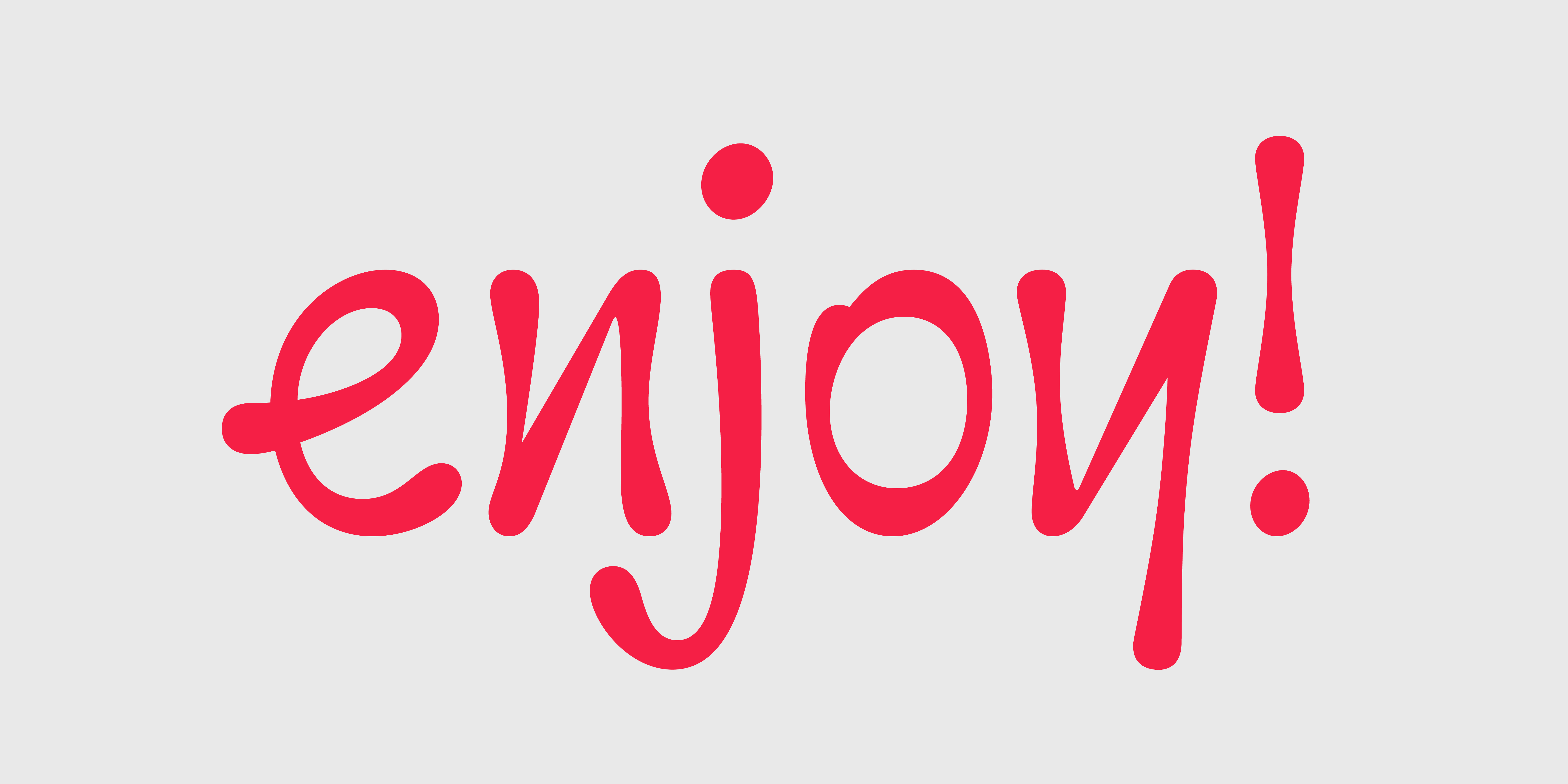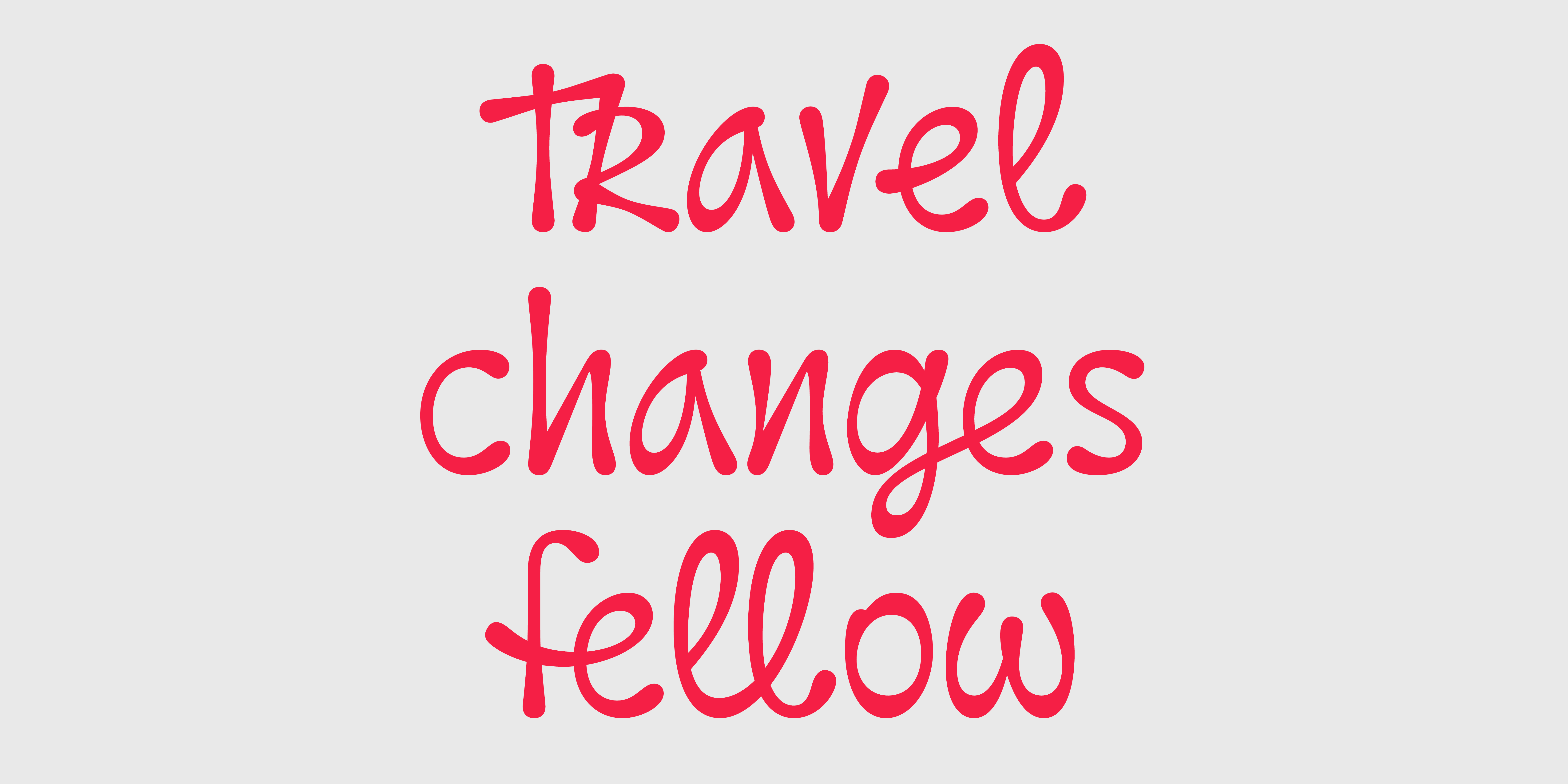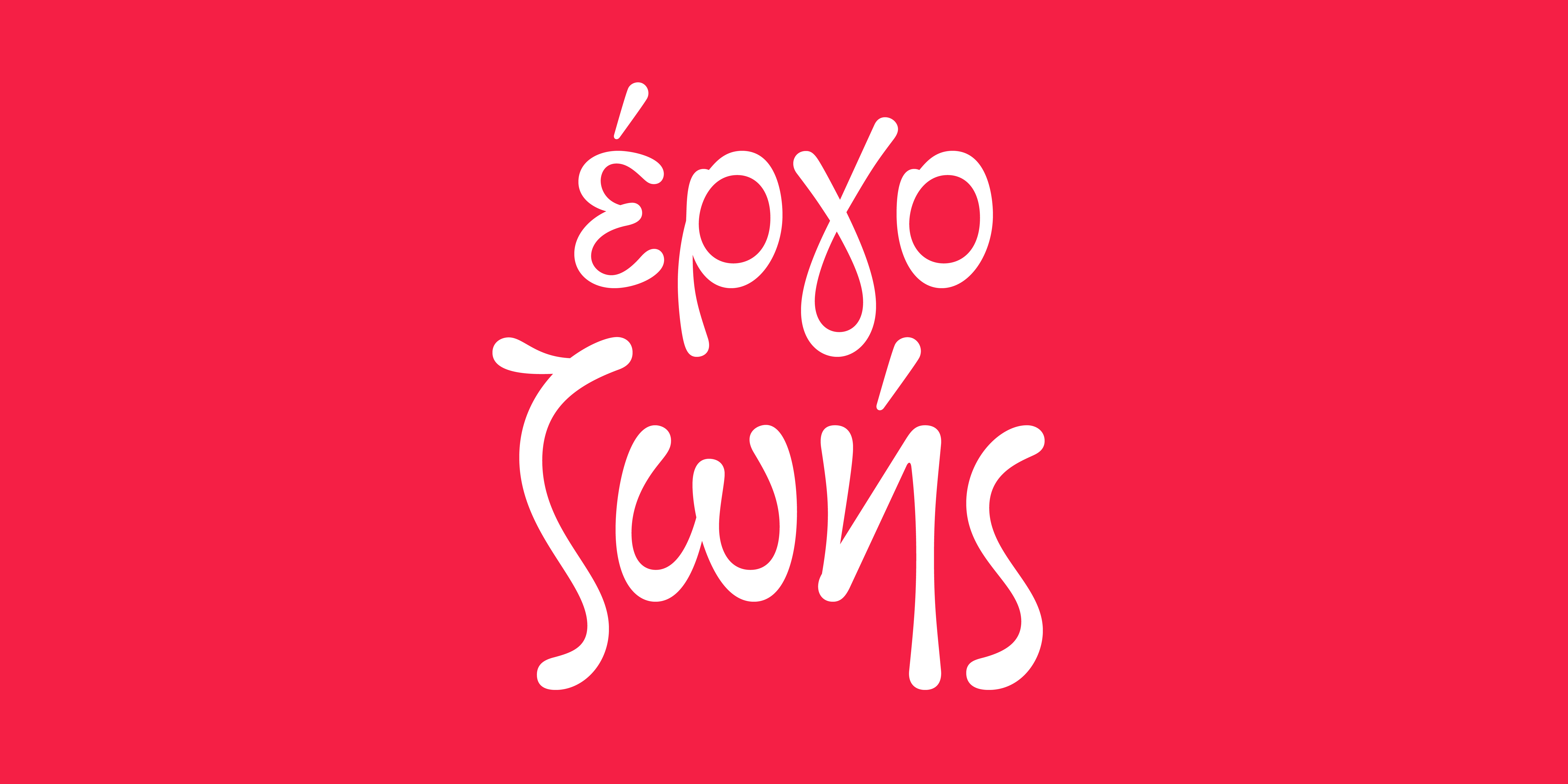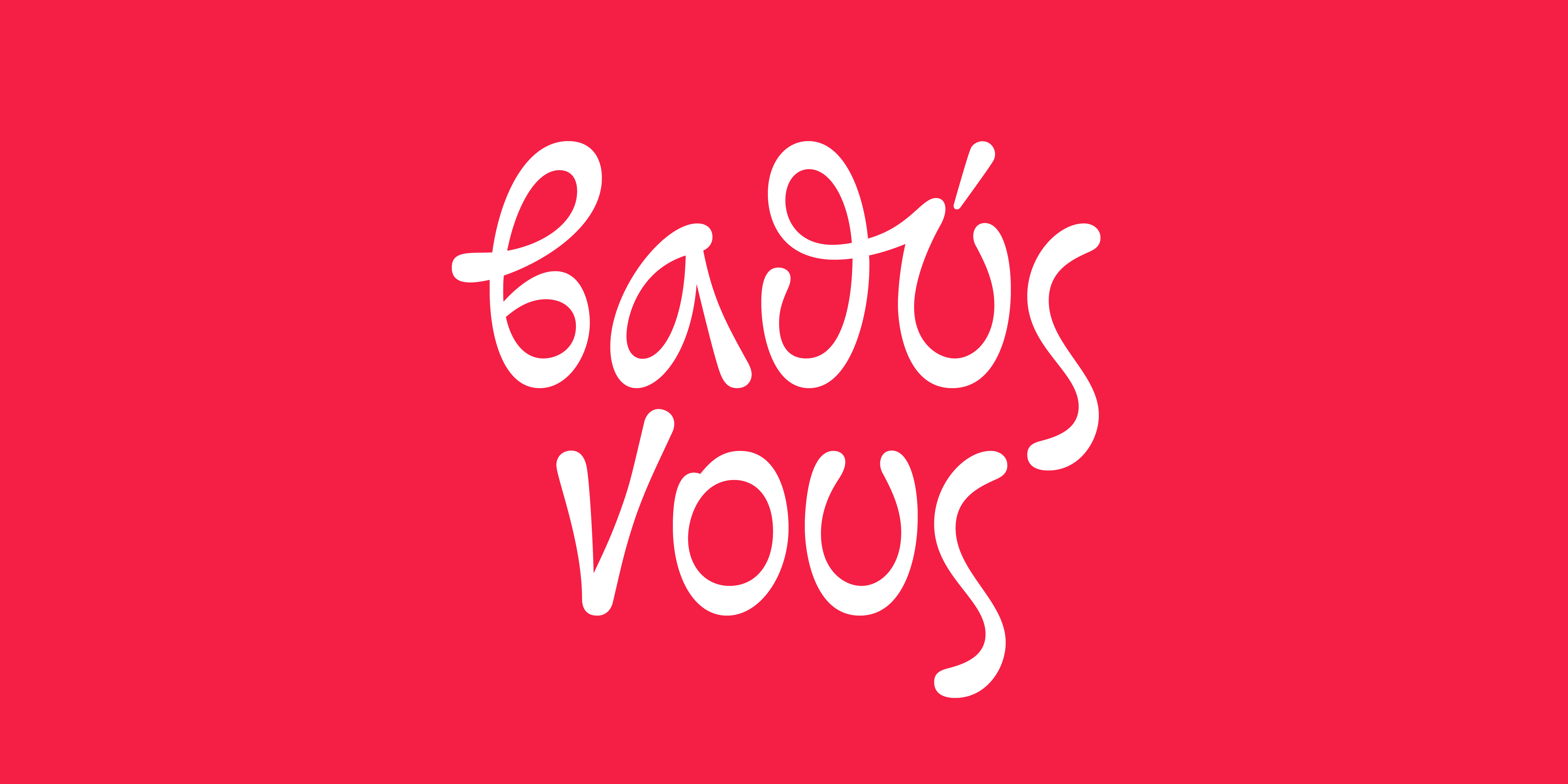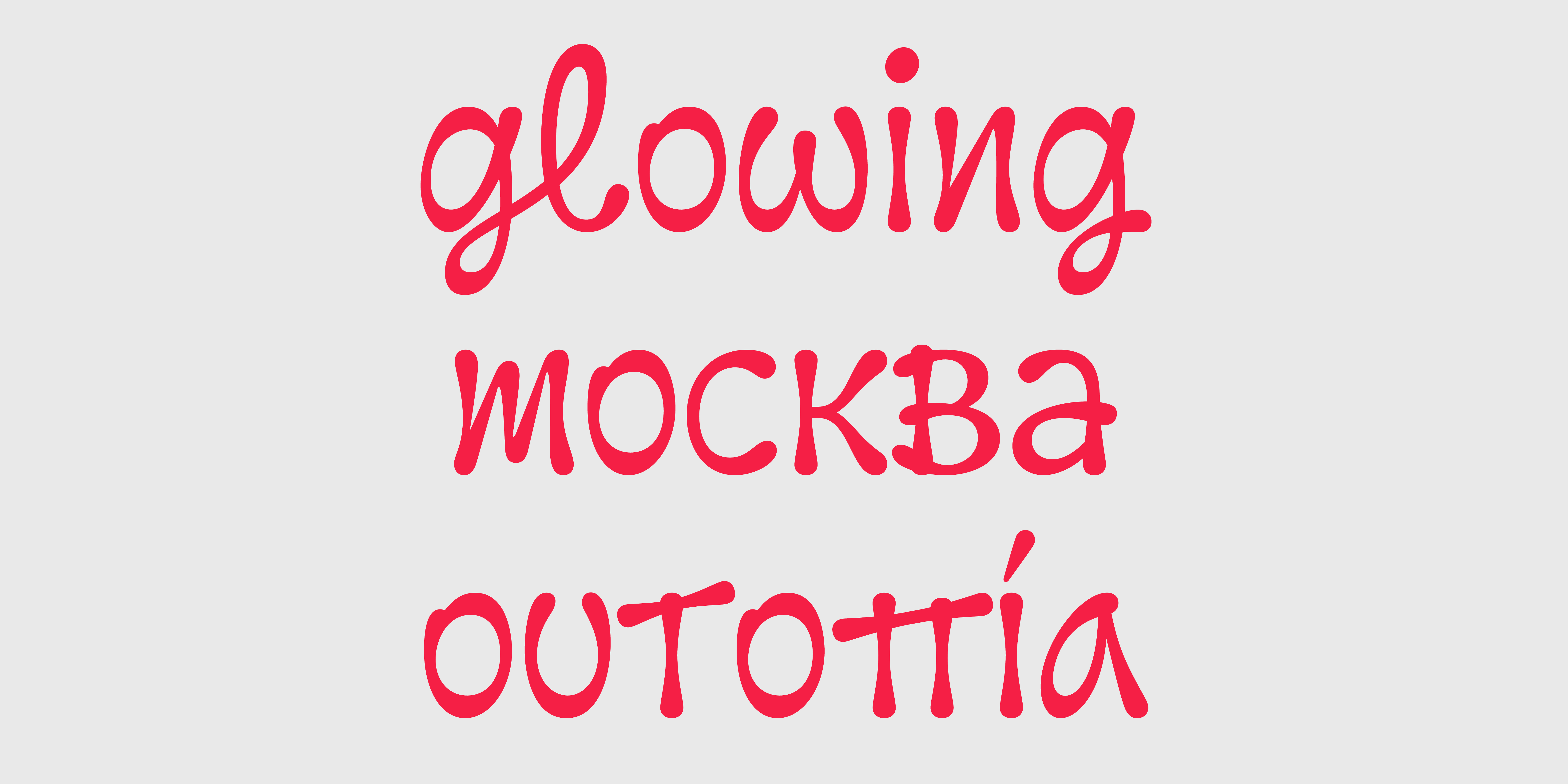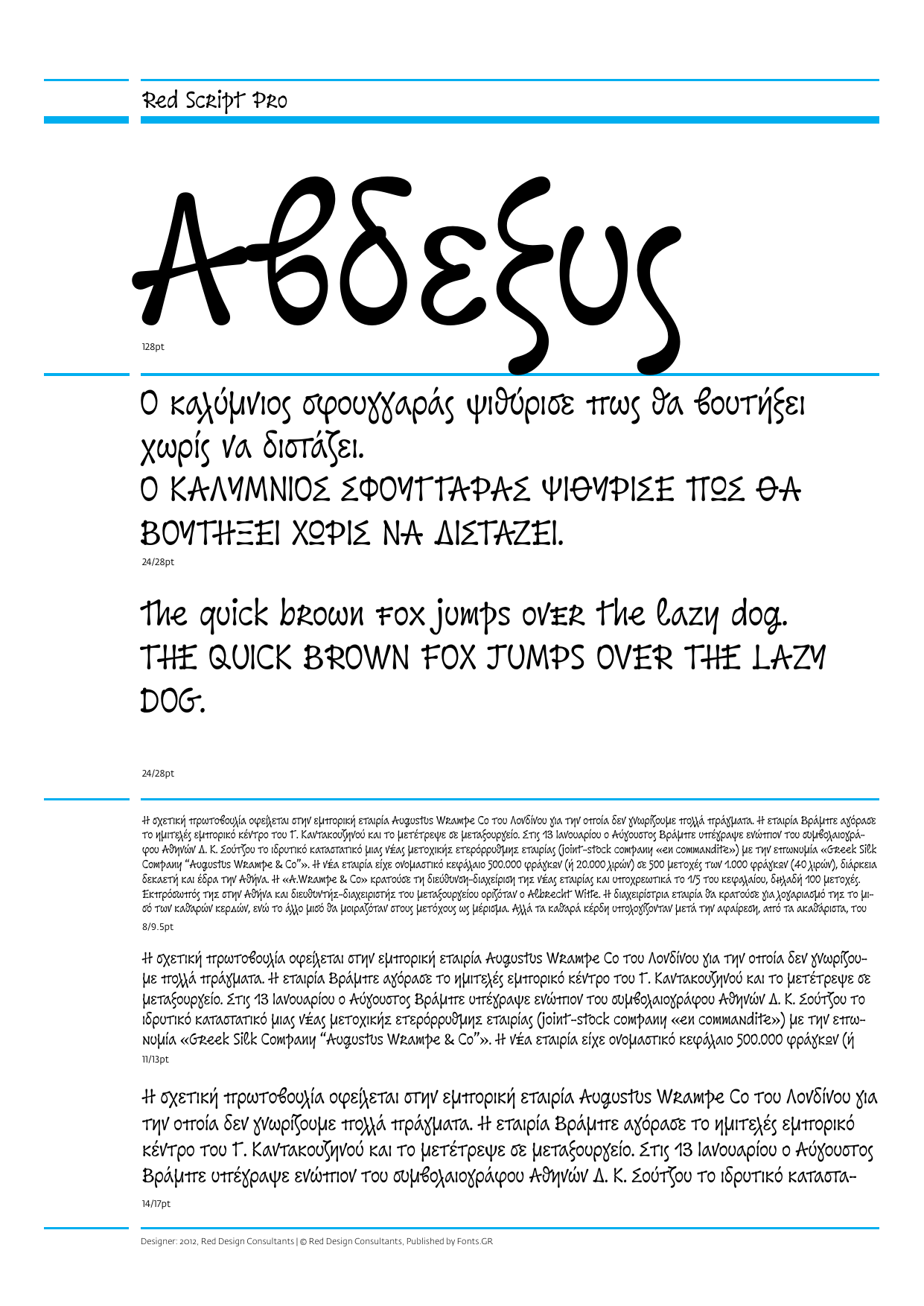
Red Script Pro
Μια πρωτότυπη γραμματοσειρά, εμπνευσμένη από τις νέες τεχνολογίες και τους εναλλακτικούς τρόπους επικοινωνίας που μας φέρνουν πιο κοντά, αρμονικά συνδυασμένων με την καλλιγραφική, ελεύθερη γραφή. Περιλαμβάνει Λατινικό, Ελληνικό και Κυριλλικό αλφάβητο και υποστηρίζει πάνω από 70 γλώσσες. Έχει πλήθος από σύνθετους (ligatures); και εναλλακτικούς (alternates); χαρακτήρες. Σχεδιασμός: Ροδάνθη Σεντούκα Εκτέλεση: Ελένη Μπεβεράτου